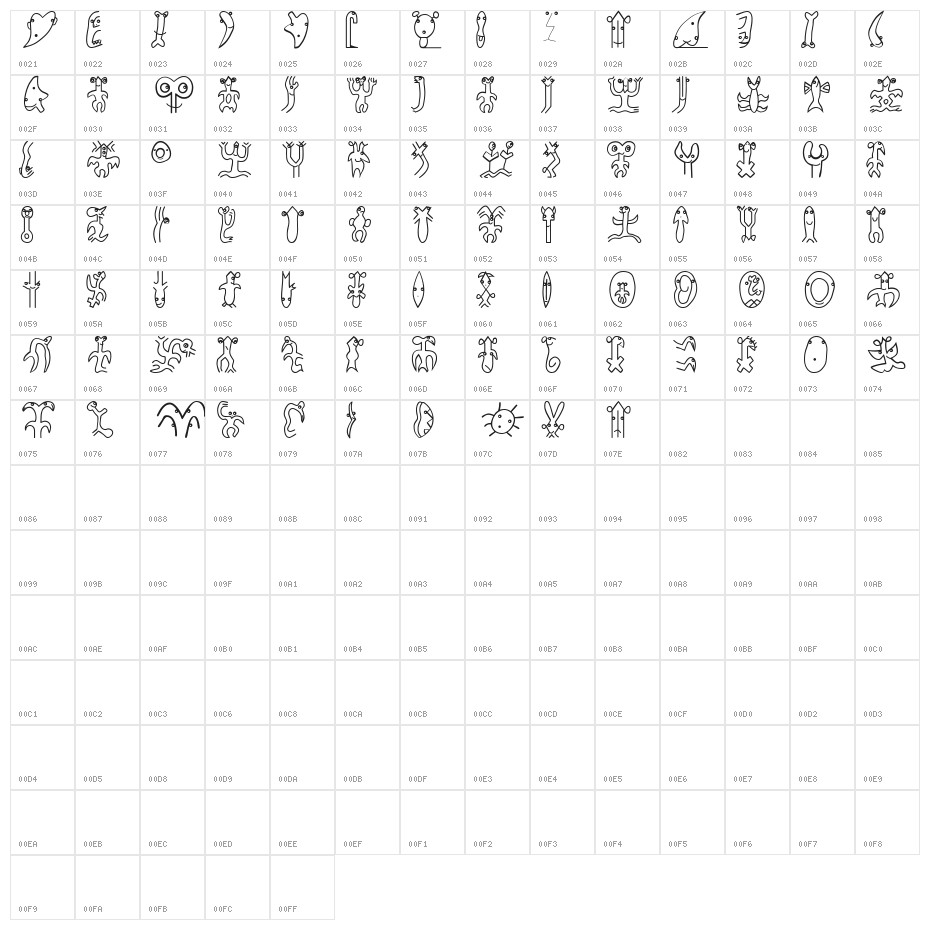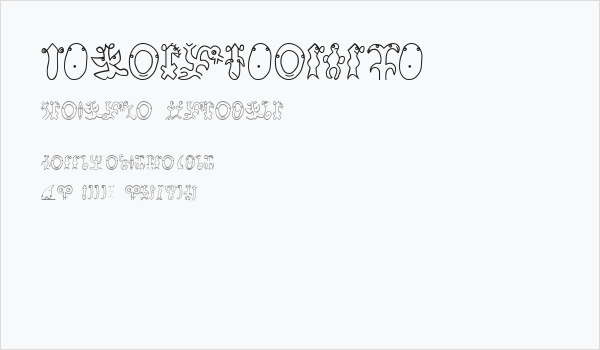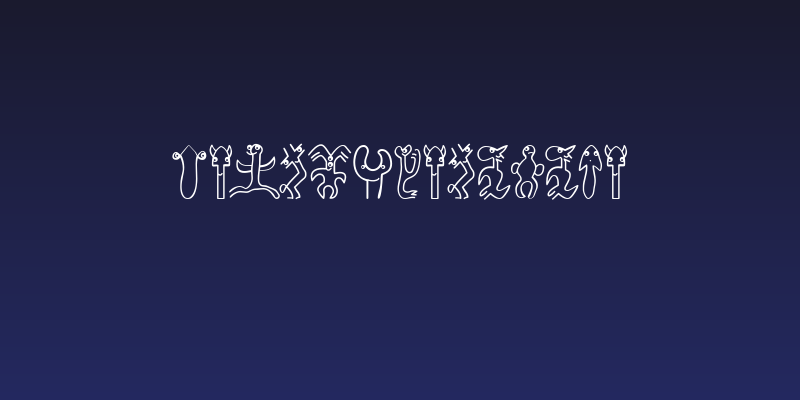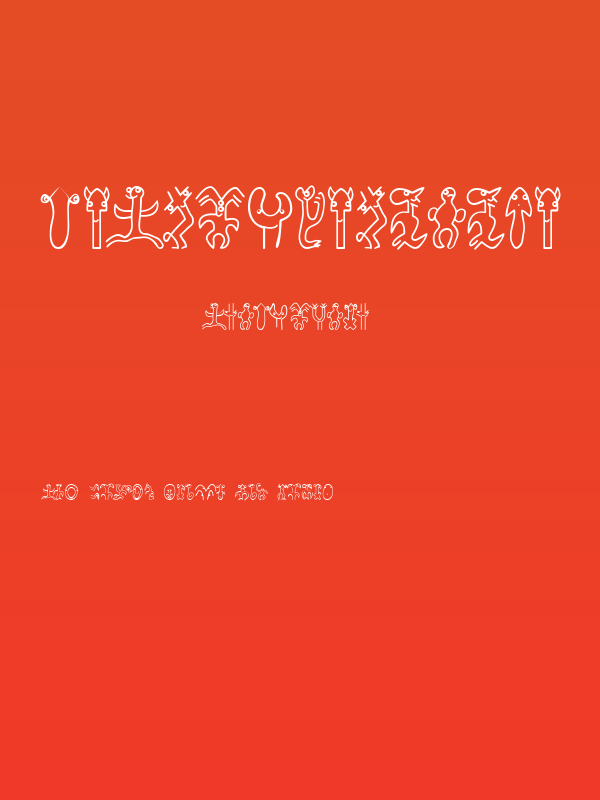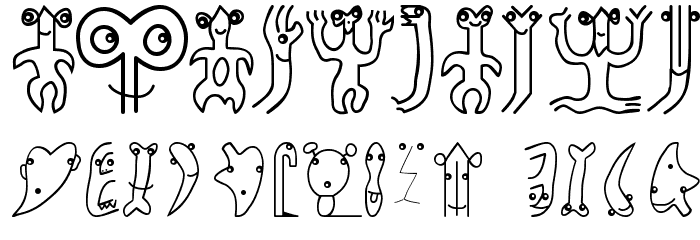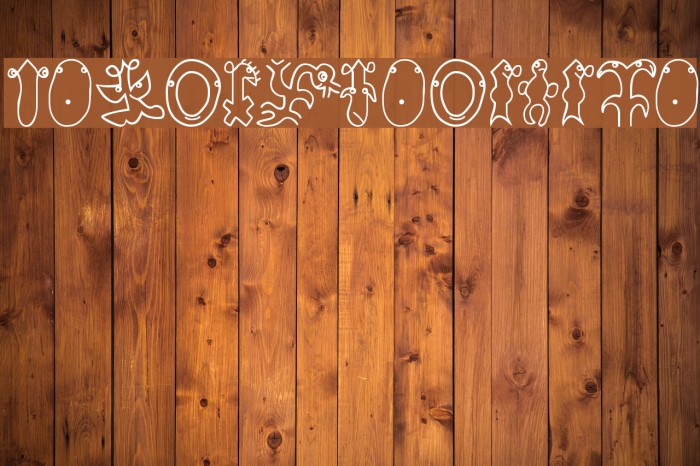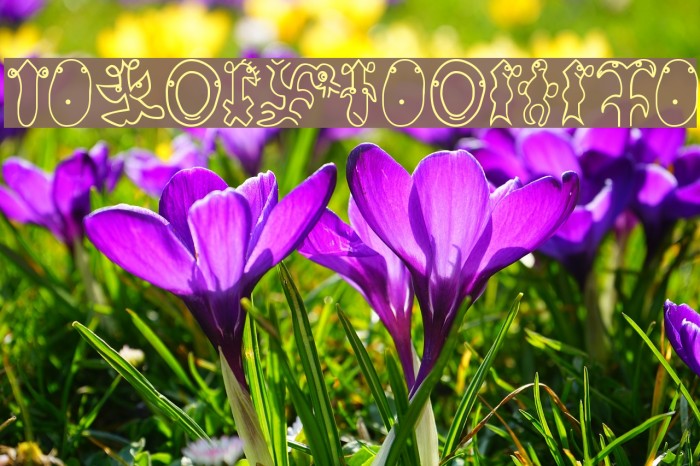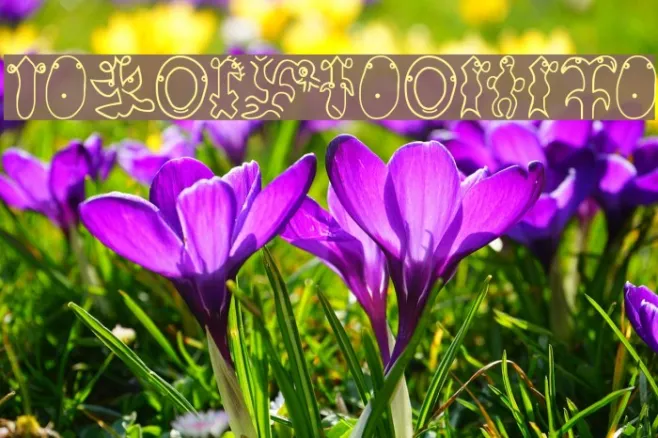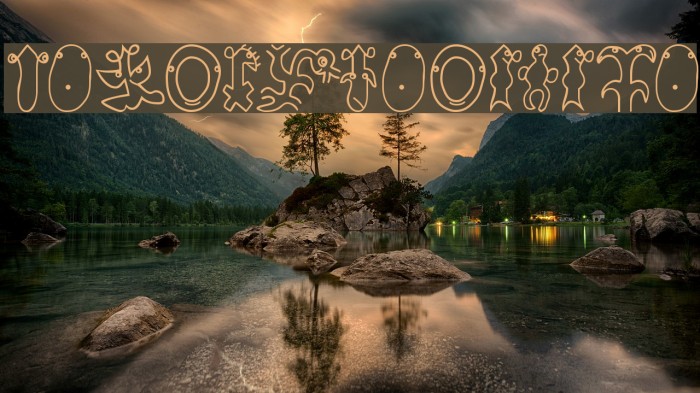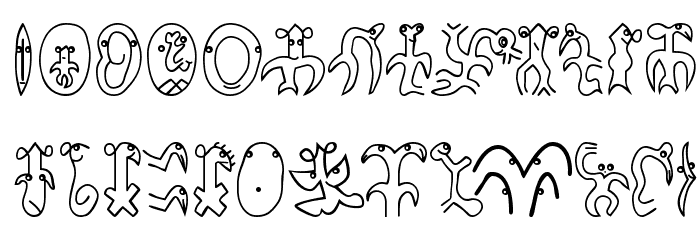
OsterinselPlus Font
| Caso d'uso | Logos, Posters, Artistic projects |
| Progetti proposti | Ideal for fantasy-themed designs, cultural exhibitions, artistic posters, or unique branding projects. |